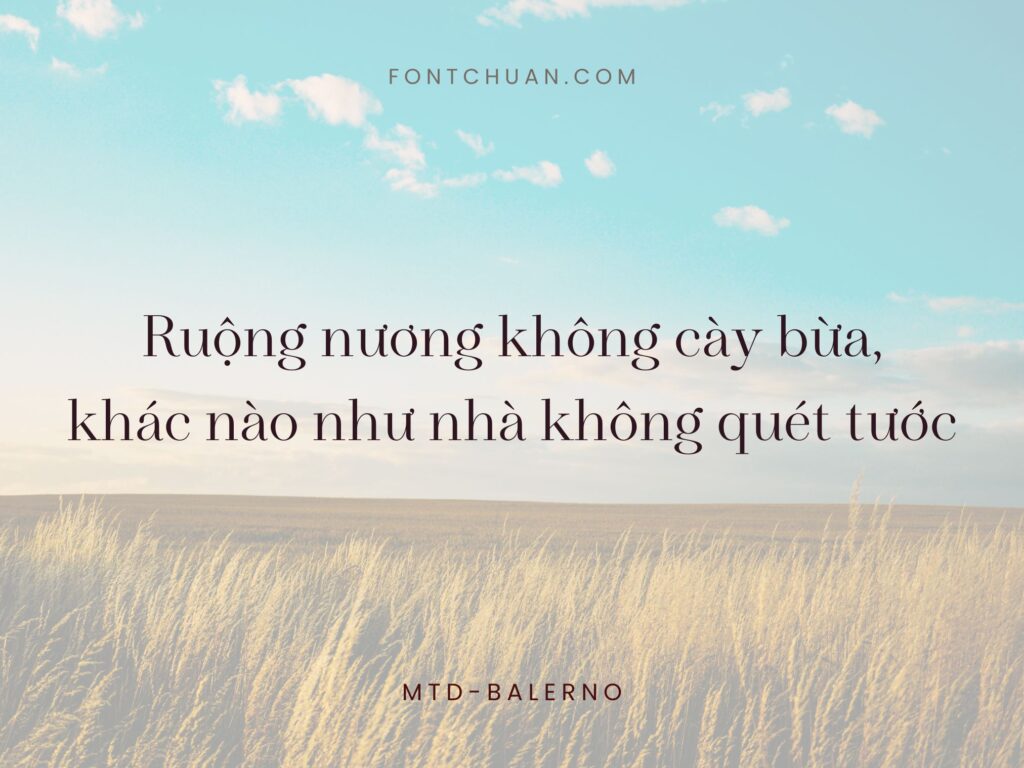
Font MTD Balerno Việt Hóa
Font MTD Balerno Regular là một kiểu chữ serif tinh tế mang hơi hướng cổ điển, được thiết kế bởi Elena Genova từ My Creative Land và đã được Việt hóa bởi Mộc Hạ. Font hỗ trợ đầy đủ tiếng Việt cùng hơn 90 ngôn ngữ khác, tạo điều kiện thuận lợi cho các dự án thiết kế đa ngôn ngữ. Đây là một phông chữ được cộng đồng thiết kế ưa chuộng và đã được các thành viên của Font Chuẩn sưu tầm, sử dụng thực tế trong nhiều ứng dụng sáng tạo như thiết kế thương hiệu, biên tập ấn phẩm và in ấn cao cấp.
MTD Balerno Regular nổi bật với các đường nét thanh mảnh kết hợp với phần chân chữ sắc sảo, tạo cảm giác sang trọng và chỉn chu. Font đặc biệt thích hợp cho các thiết kế logo, tiêu đề sách, bìa tạp chí, bao bì sản phẩm cao cấp, thiệp cưới và các sản phẩm đòi hỏi thẩm mỹ cao. Các ngành nghề phù hợp gồm quảng cáo, giáo dục, công nghệ, thiệp cưới và ảnh cưới. Đồng thời, font cũng được áp dụng hiệu quả trong các dịp như Tết, Giáng sinh, Valentine và các sự kiện mang tính nghệ thuật và trang trọng.